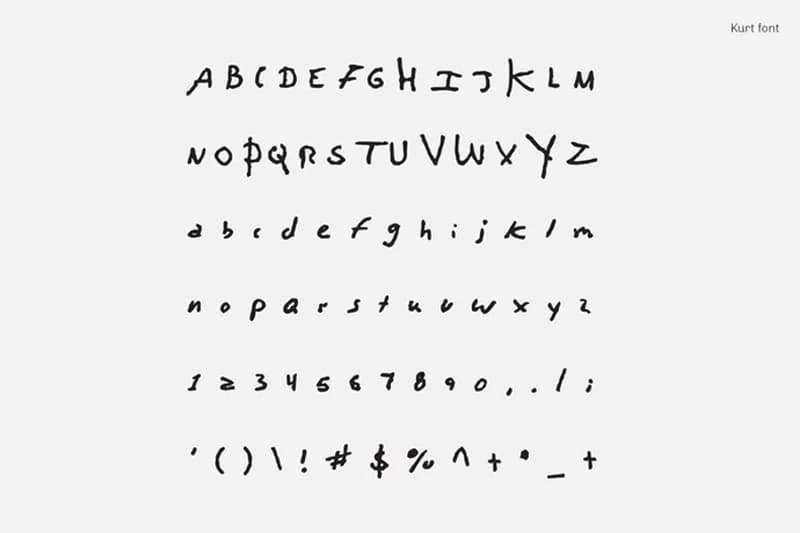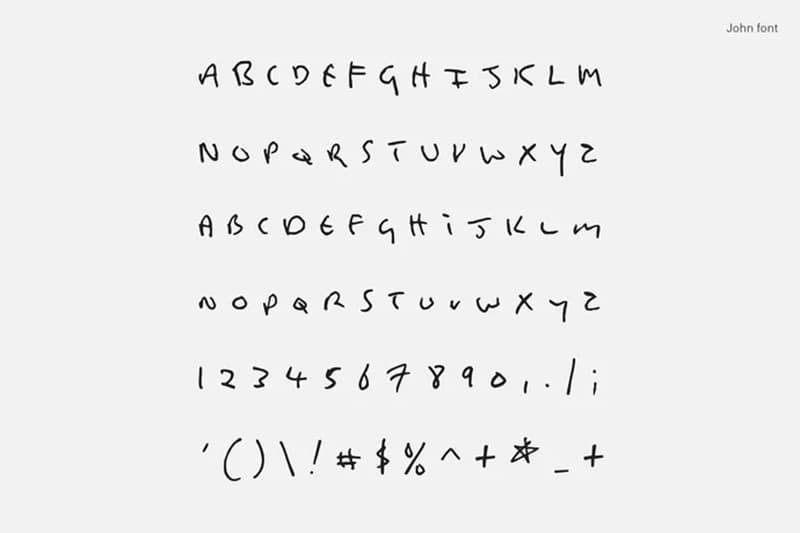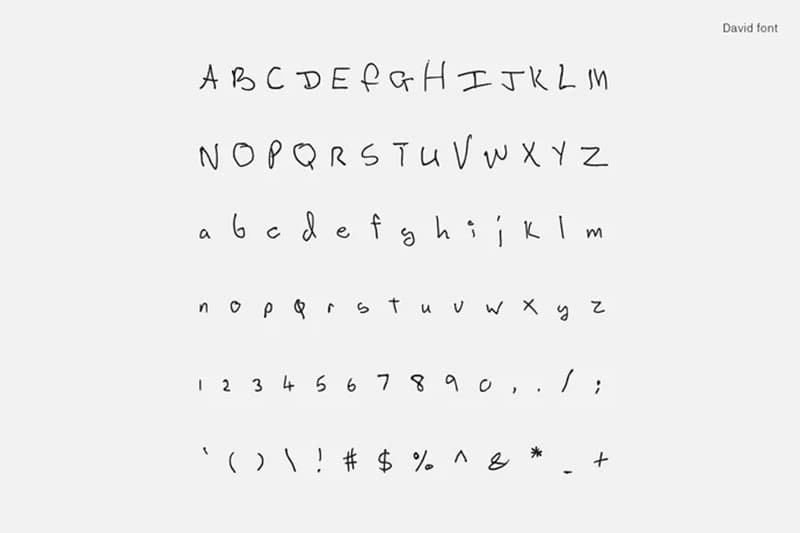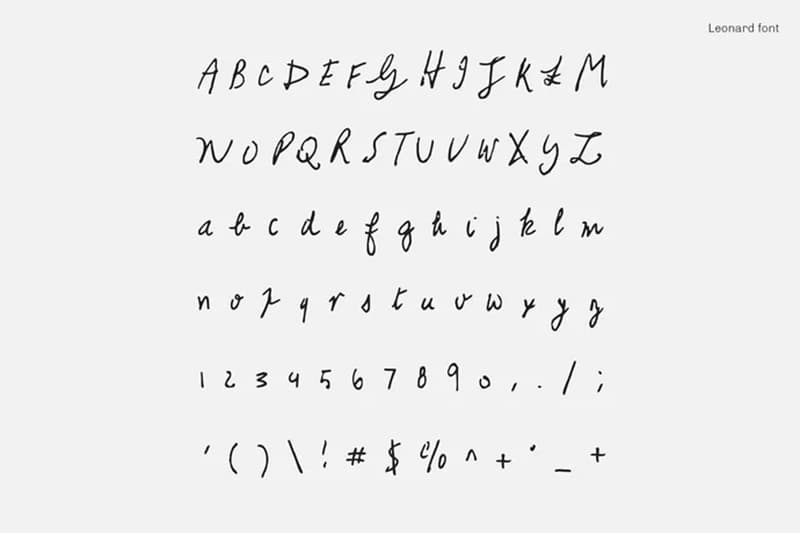
Kurt Cobain 等已故乐人字体现已可供下载
各位觉得这样的作为是好是坏?
Kurt CobainDavid BowieJohn LennonLeonard Cohen 等已故音乐人除了留给后是无限的音乐贡献之外,他们在时装、艺术等领域也有莫大的影响。近日,设计师 Nicolas Damiens 和 Julien Sens 便参考了以上四位音乐人的笔迹,创作出一系列可以下载使用的字体。他们以这些人的笔记、信件以及 Kurt Cobain 的遗书为范本,设计出了特别的字样,甚至表示 Kurt Cobain 的字体充满诗意。不过也有网友表示这两位设计师毫不尊重亡者,不晓得各位如何看待此事?当然,有意下载这些字体的朋友我们也为你准备好了连结